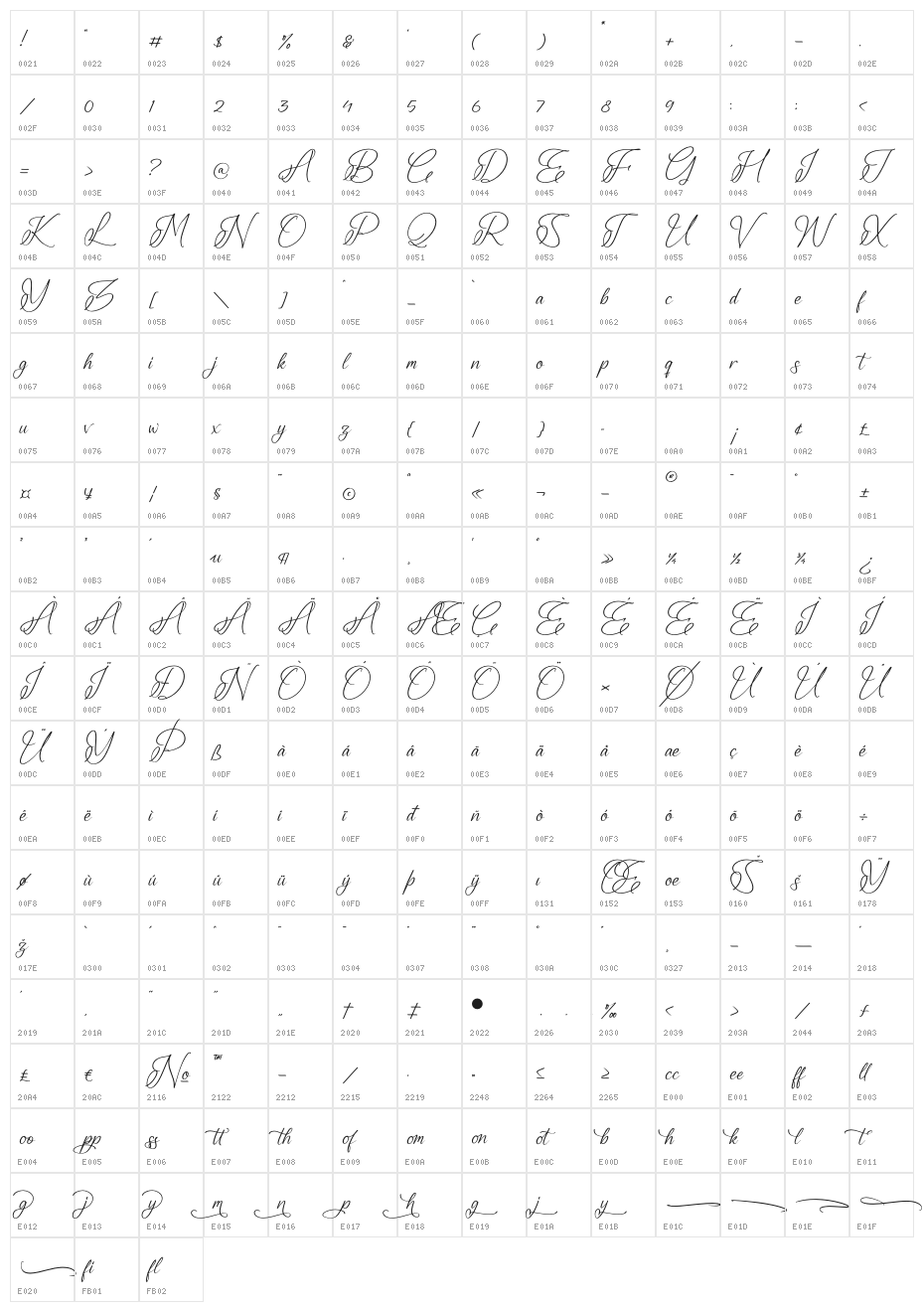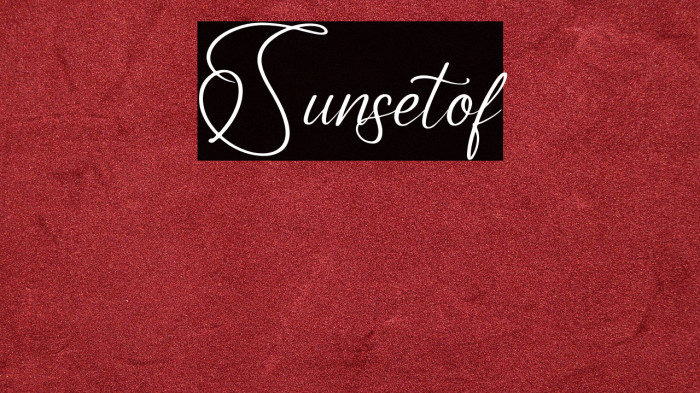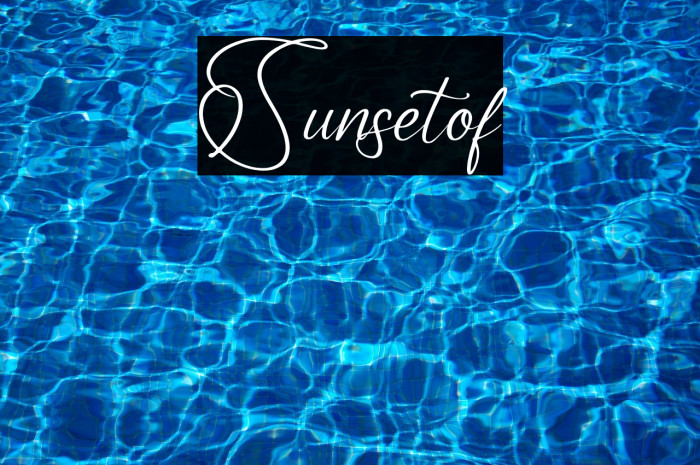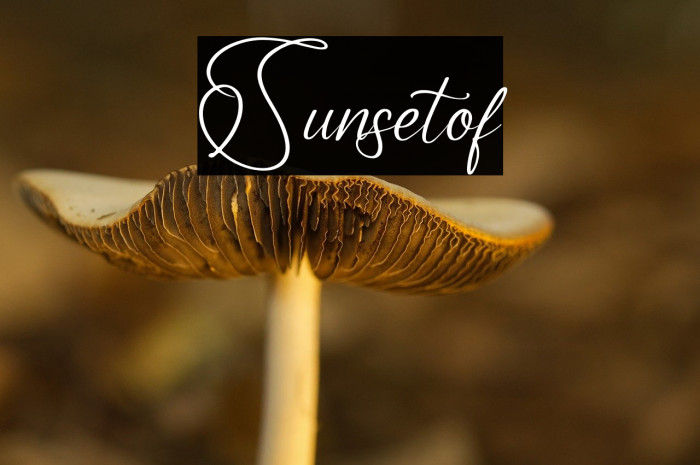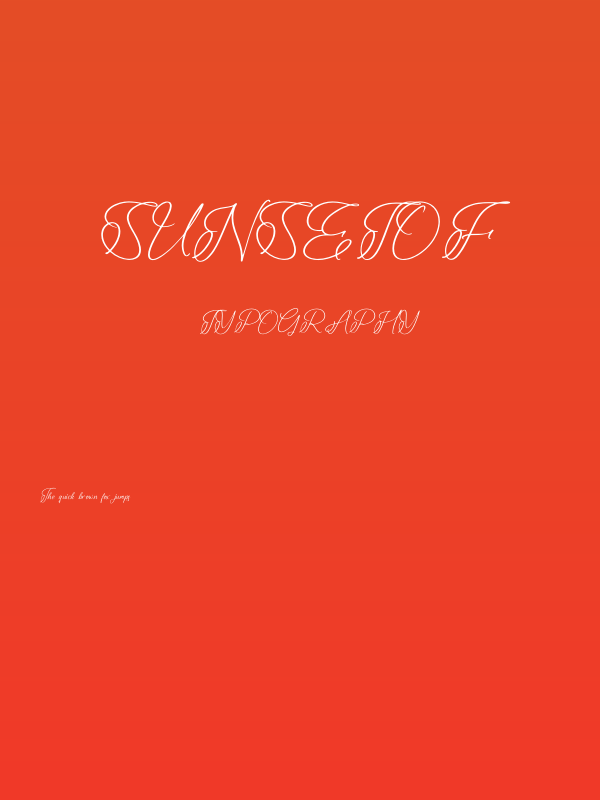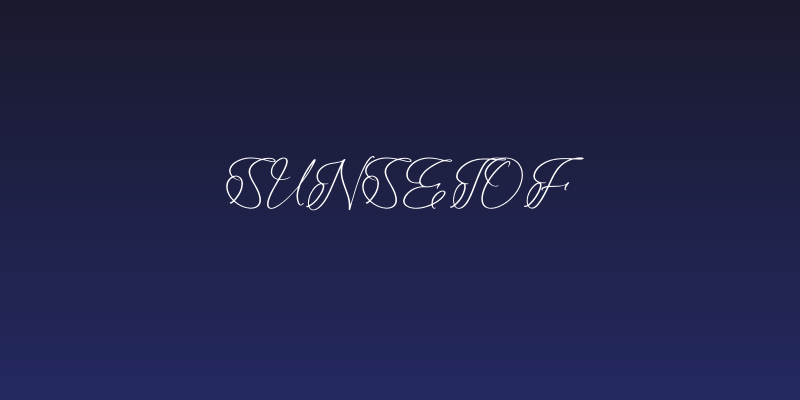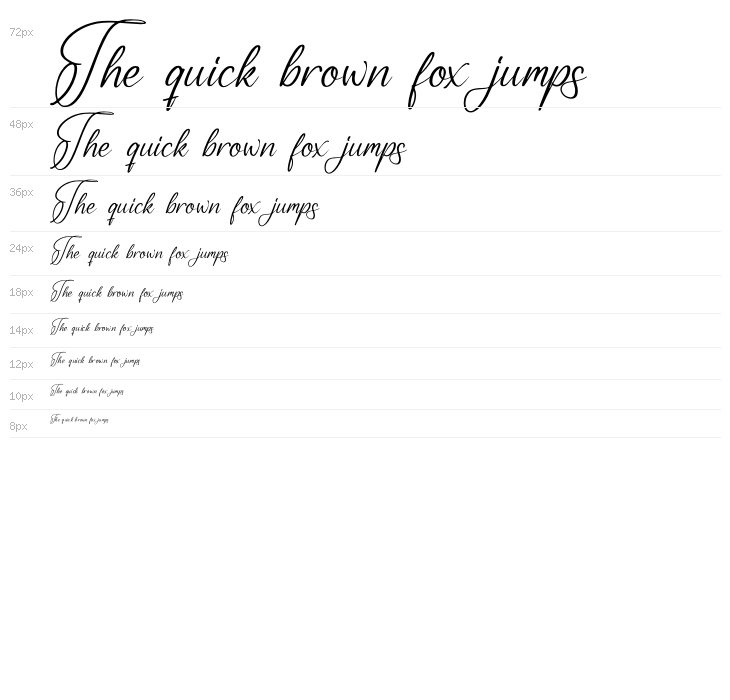
Sunsetof Font
| Stile generale | Elegant, Decorative |
| Caso d'uso | Logos, Invitations, Branding |
| Progetti proposti | Ideal for wedding invitations, luxury branding, elegant stationery, and high-end product packaging. |